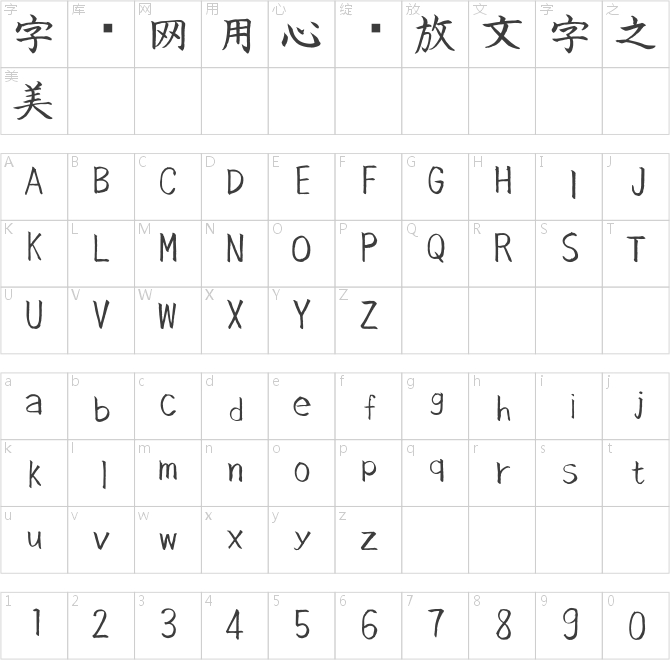
英椎楷書ackaisyo 詳情頁
字體名稱: 英椎楷書ack
英椎楷書ackaisyo
英椎楷書是日本acfont自己手寫開發(fā)的一款字體,這款字體端莊雄偉,書寫工整,是一款十分好看的手寫字體。英椎楷書共收錄了6879個文字,因為日文字符一般是以JIS水準(zhǔn)為標(biāo)準(zhǔn),所以繁體字支持得比較完整。簡體字?jǐn)?shù)相對較少,不過也確實是一款難得的字體。喜歡的朋友趕緊下載吧!